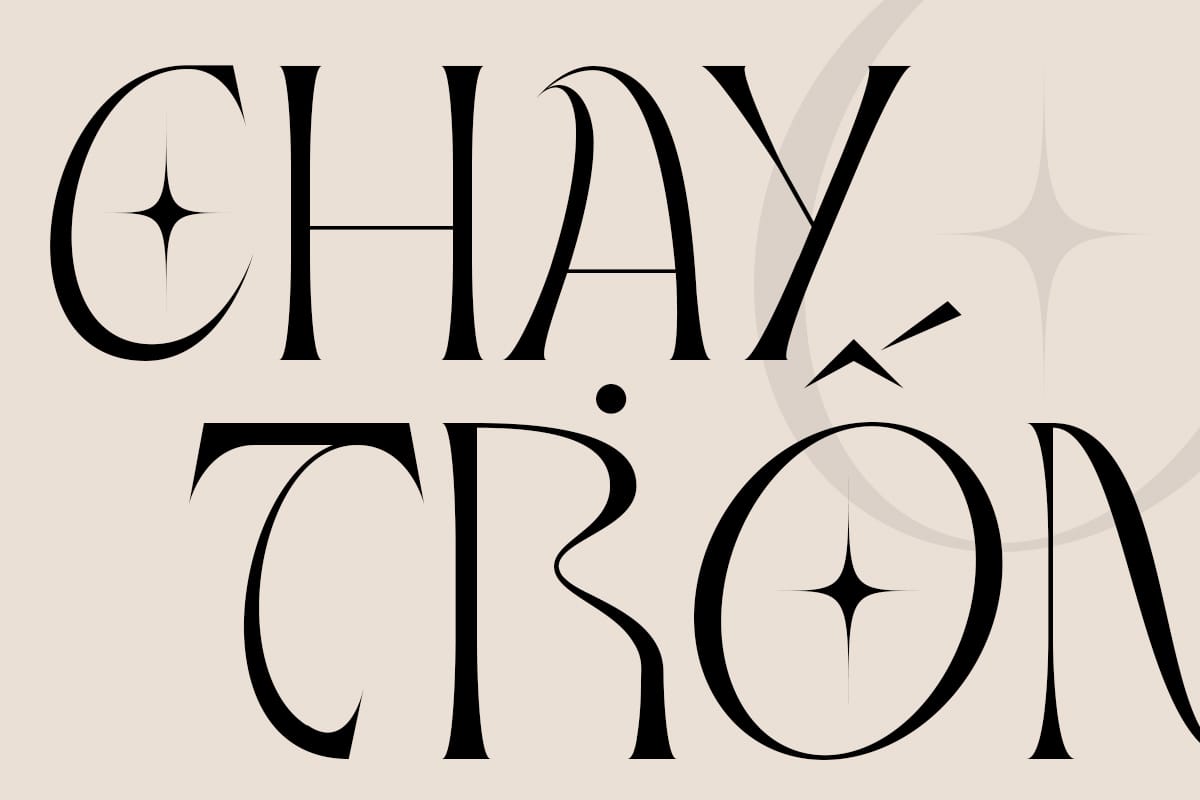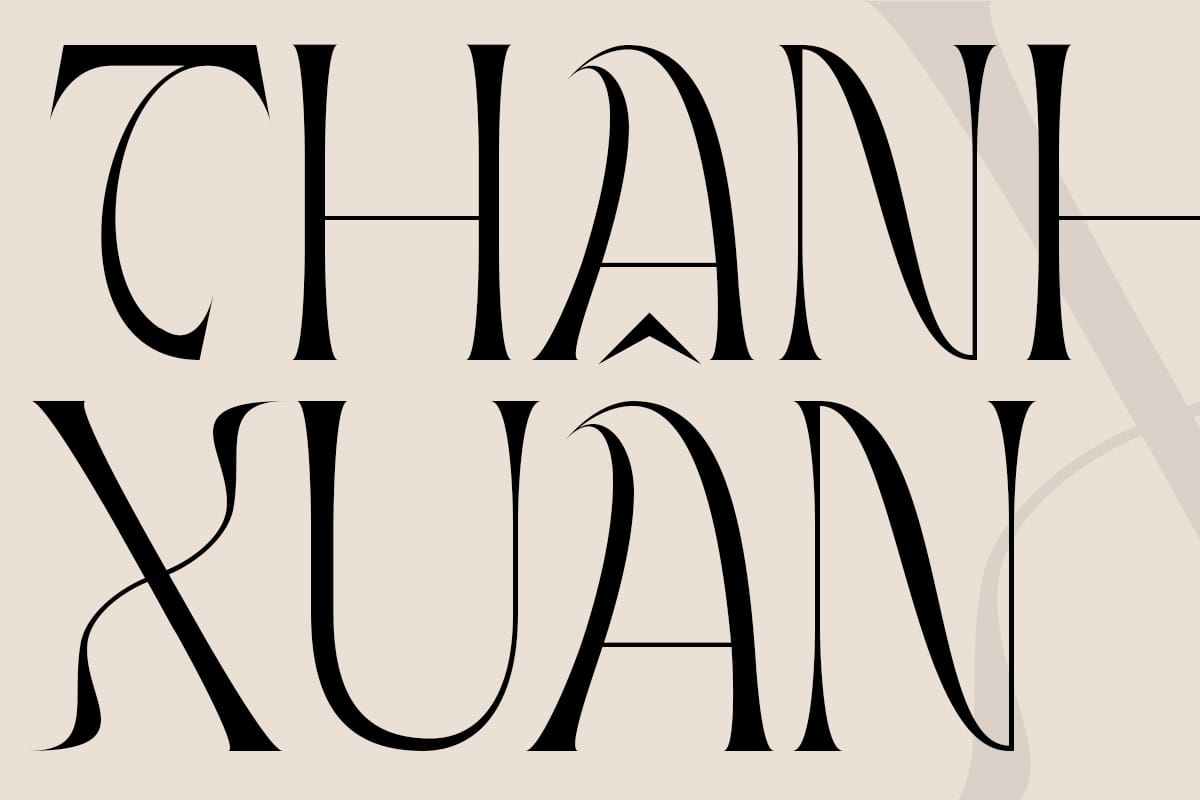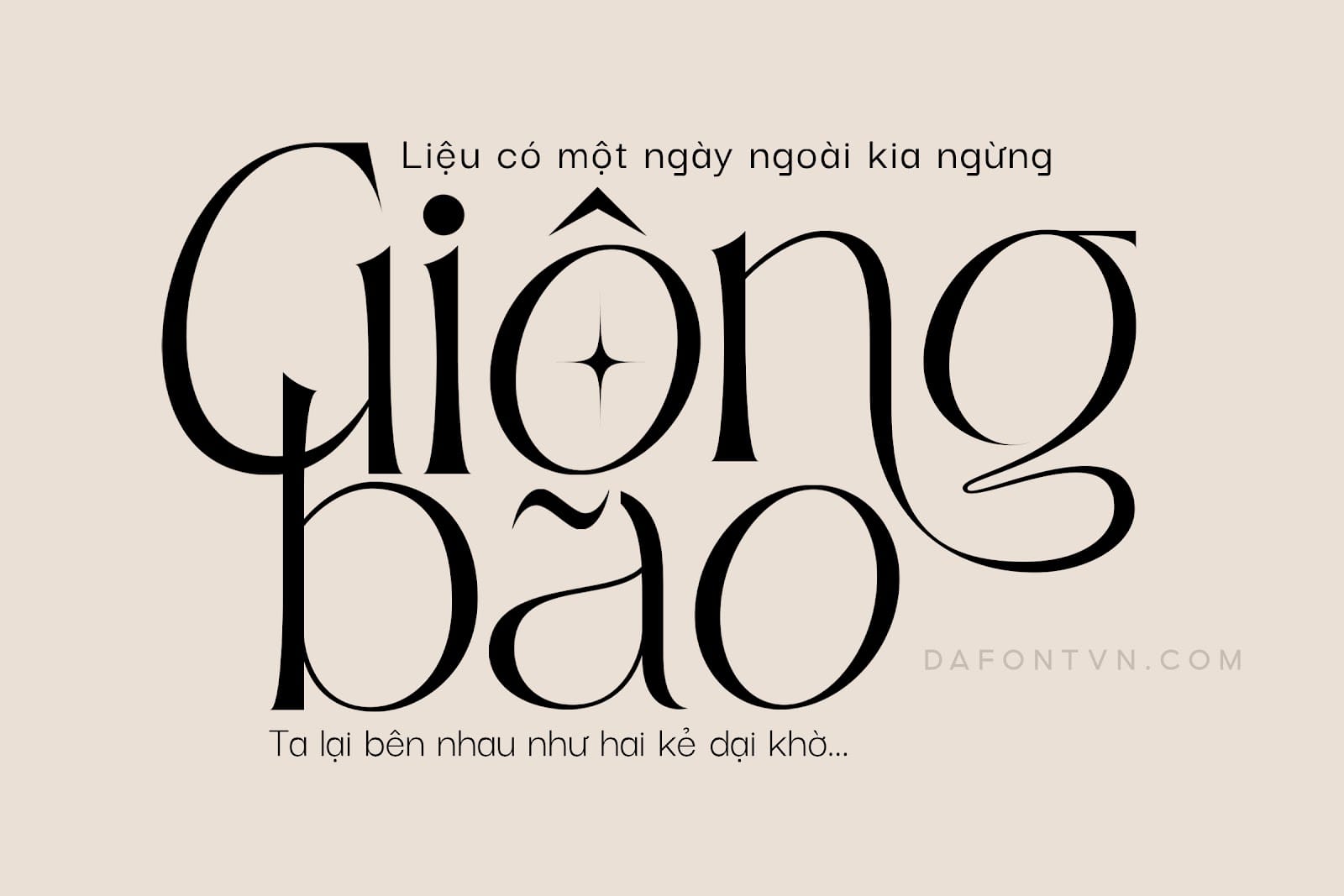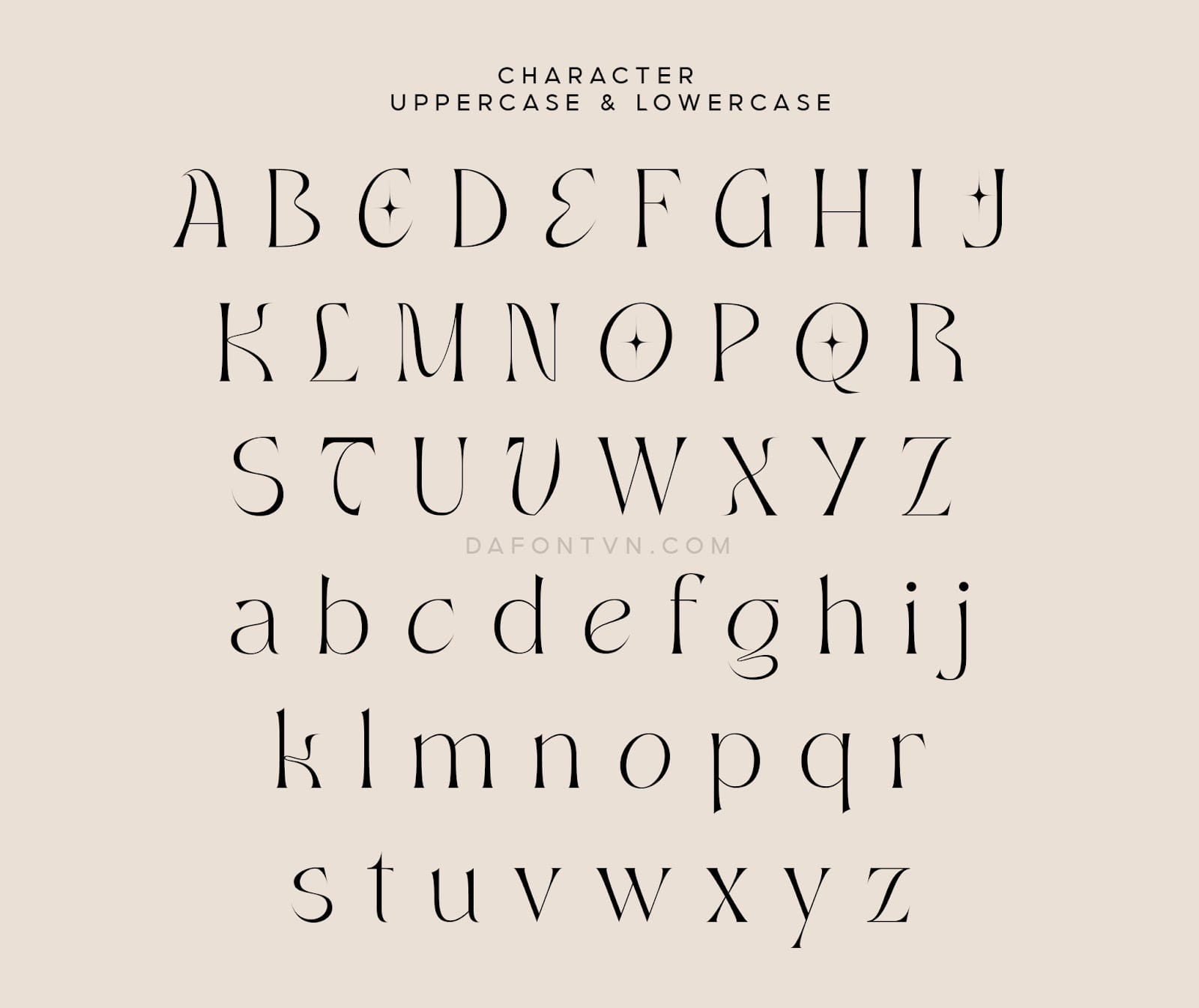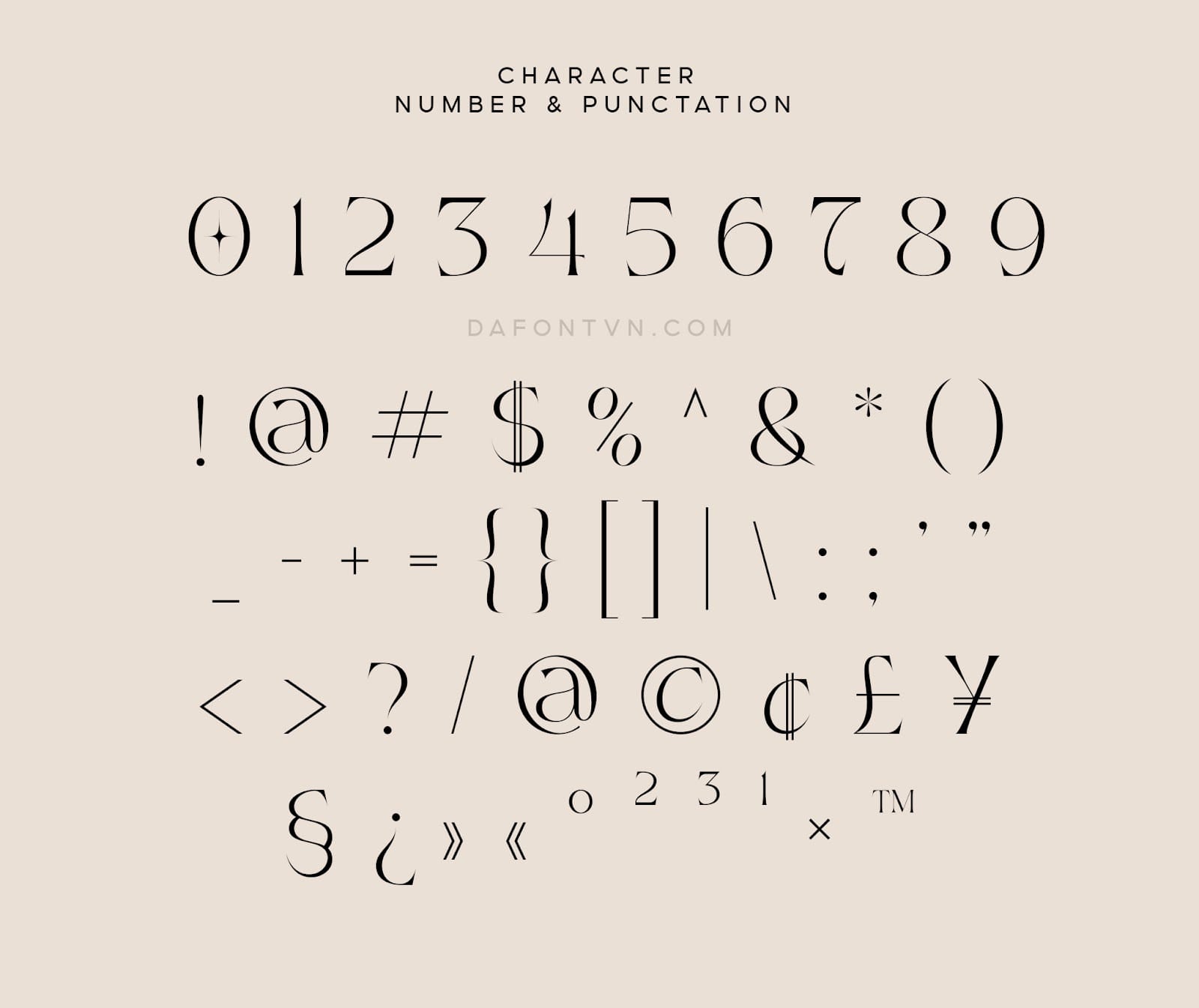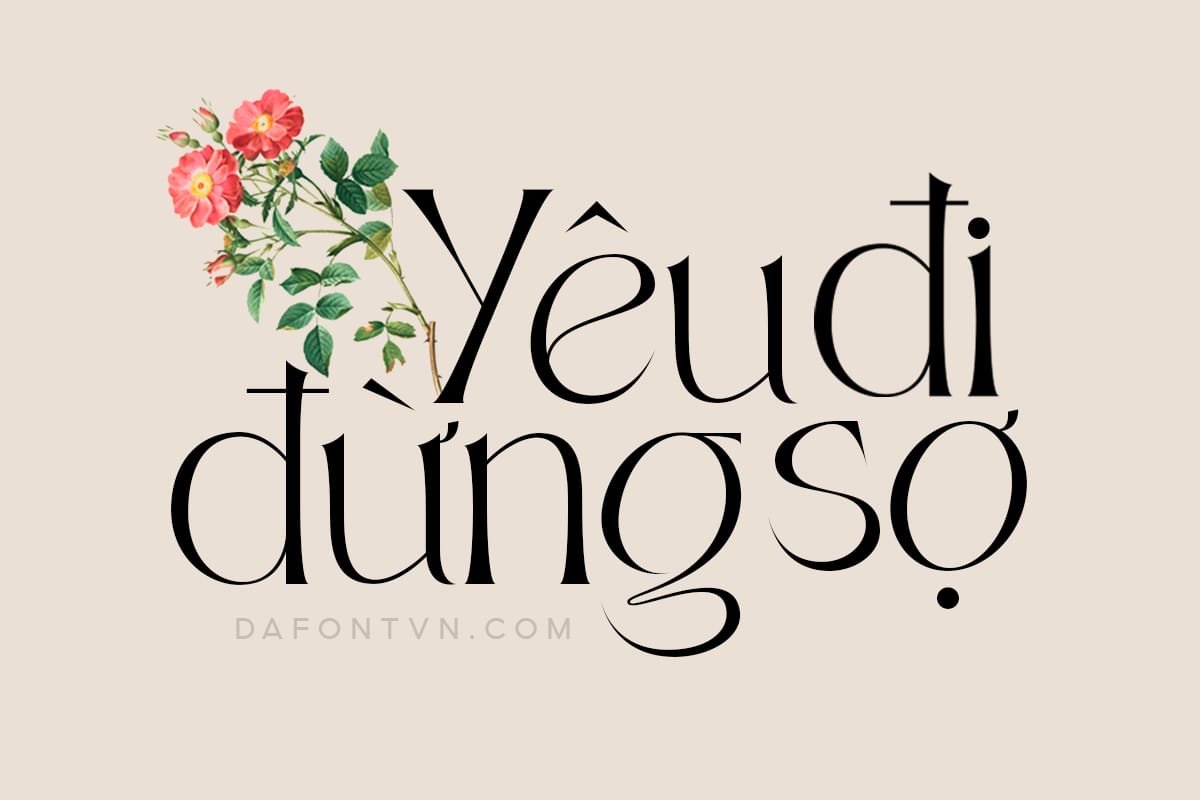
Font Onteal là một kiểu font mang phong cách hiện đại với các nét chữ được thiết kế độc đáo dễ dàng mang lại cho bạn các thiết kế cực kỳ ấn tượng. Đi kèm với hơn 72 chữ ghép đặc biệt, font phù hợp cho nhiều các thiết kế khác nhau như logo, thương hiệu, typography…Font Onteal việt hóa đầy đủ, kerning, tối ưu lại font cũng như chỉnh sửa lại 1 số dấu và mã hóa PUA để bạn có thể sử dụng dễ dàng trên bất kỳ phần mềm nào.